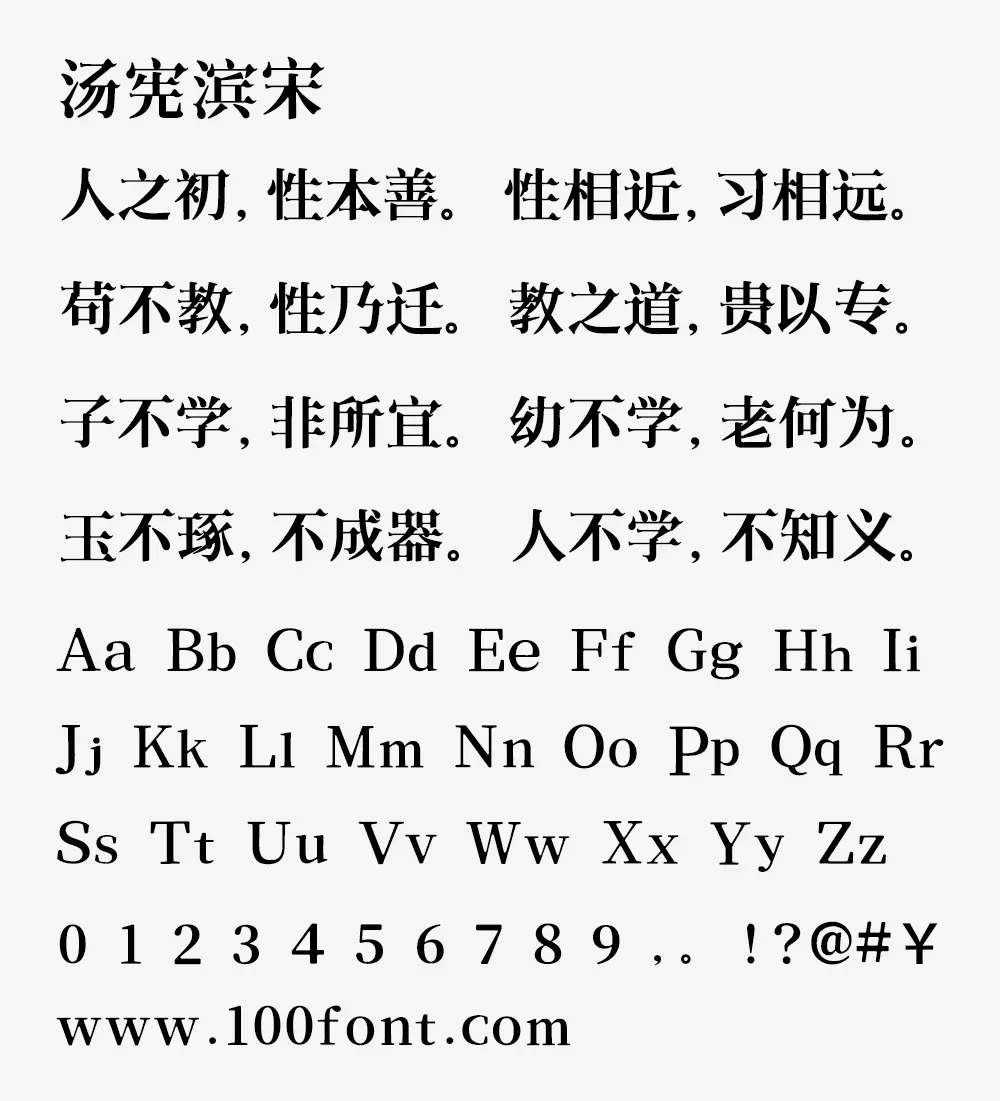
湯憲濱宋,依據“思源宋體”進行改變,本款設計是哥特式與宋體的結合,形成時尚靚麗的視覺感知,其筆畫遒勁靈動,連筆張弛有度,整體清麗優美,是標題和廣告語等用字的更多選擇。
把經典的宋體有所豐富視覺的改變,製作字體庫3500常用字。源於在平面設計中很多要收費商用,以已微弱個人之力,修改調整5遍,奉上各位免費自由商用。